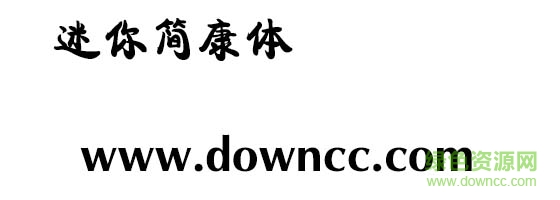
迷你簡(jiǎn)康體是一款應(yīng)用于設(shè)計(jì)方面的簡(jiǎn)體中文漢字,該字體偏粗,但結(jié)構(gòu)清晰,風(fēng)格統(tǒng)一,可適用于廣告設(shè)計(jì)、平面設(shè)計(jì)、印刷包裝、書法繪畫等領(lǐng)域,喜歡的朋友快下載收藏吧。